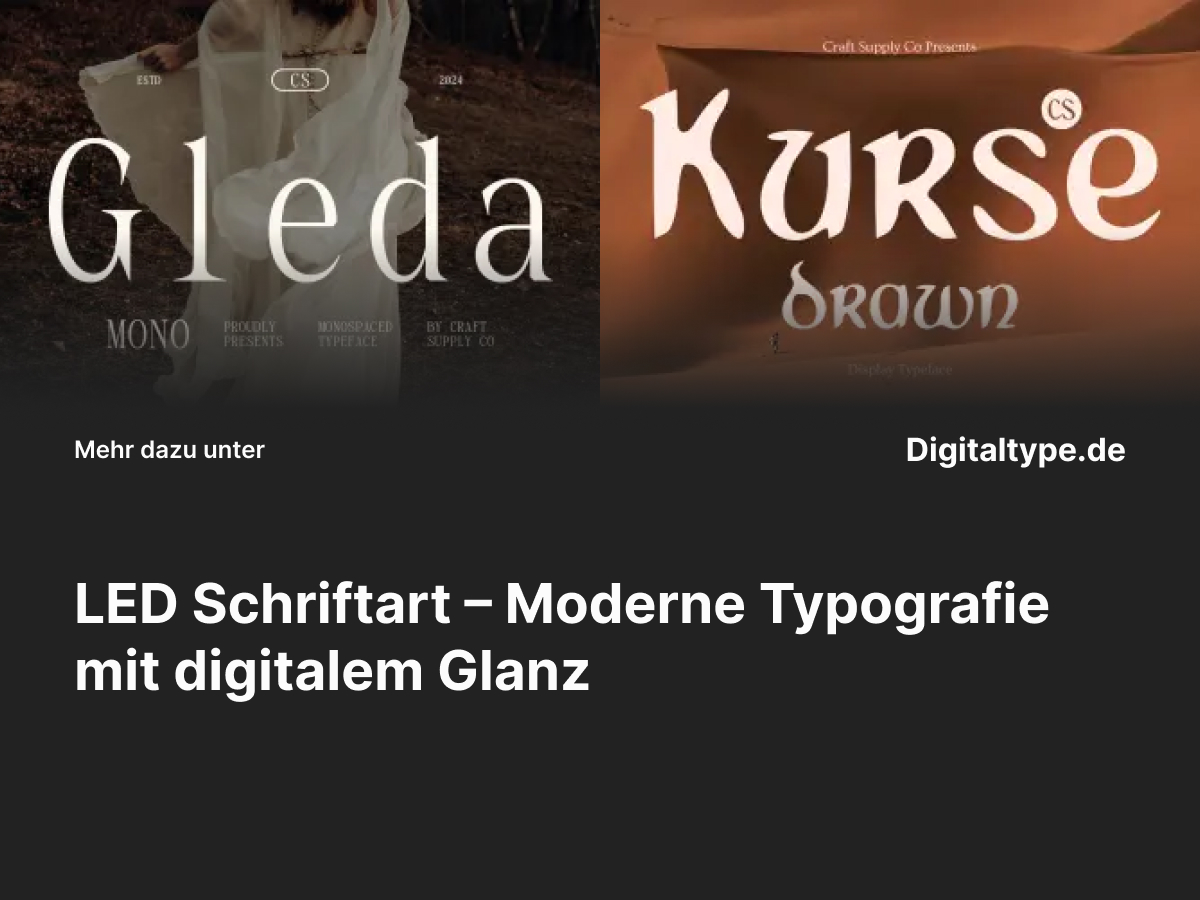
Eine LED Schriftart steht für Innovation, Technologie und futuristisches Design. Inspiriert von den leuchtenden Punkten und Linien digitaler Anzeigen, vermitteln diese Fonts ein modernes, technisches und professionelles Erscheinungsbild. Sie sind ideal für Projekte, die einen futuristischen Look, klare Struktur und Aufmerksamkeit durch leuchtende Formen suchen. In diesem Artikel stellen wir dir die besten LED-Schriftarten vor und zeigen, wie du sie optimal einsetzen kannst.
Was ist eine LED Schriftart?
Eine LED Schriftart imitiert den Stil elektronischer Leuchtdioden, wie man sie von Werbetafeln, Digitaluhren oder Displays kennt. Ihre Buchstaben bestehen häufig aus segmentierten Linien oder Punkten, die an leuchtende Pixel erinnern. Das Ergebnis: ein Schriftbild, das zugleich technisch, modern und aufmerksamkeitsstark wirkt.
LED Fonts eignen sich besonders für Branding, Gaming-Logos, Webdesigns oder Event-Plakate mit futuristischem Touch. Sie erzeugen Dynamik, Energie und ein Gefühl digitaler Innovation – perfekt, um moderne Zielgruppen anzusprechen.
Wann du LED Schriftarten verwenden solltest
- ✔️ Für Logos und Designs mit technologischem oder futuristischem Charakter.
- ✔️ In Gaming-, Musik- oder Event-Projekten, die mit Licht und Bewegung arbeiten.
- ✔️ Für digitale Werbungen, Displays und Webseiten mit modernem Erscheinungsbild.
- ✔️ In kreativen Branding-Projekten, die Innovation und Energie ausstrahlen sollen.
Eine LED Schriftart verleiht jedem Design ein leuchtendes, zeitgemäßes Erscheinungsbild – besonders effektiv in dunklen Farbschemata oder mit Neon-Effekten.
Die 7 besten LED Schriftarten für Designer
Hier sind sieben beeindruckende LED Schriftarten, die digitales Leuchten, klare Linien und kreative Energie perfekt vereinen. Jede davon eignet sich ideal für Projekte mit einem modernen, technologischen oder futuristischen Fokus.
1. CS Gleda Mono – Monospaced Font
CS Gleda Mono bietet ein präzises, technisches Design mit gleichmäßigen Abständen – ideal für LED-Displays und digitale Typografie. Perfekt für UI/UX-Projekte und moderne Branding-Konzepte.
2. CS Kurse – Drawn Font
CS Kurse kombiniert einen handgezeichneten Look mit klarer, futuristischer Struktur. Diese Schrift eignet sich hervorragend für kreative Designs mit digitalem Flair und modernem Ausdruck.
3. CS Gianluca – Messy Handwritten Font
CS Gianluca bringt eine organische Note in den LED-Stil. Ihr unregelmäßiger, handschriftlicher Charakter wirkt lebendig und modern zugleich – eine perfekte Mischung aus Technik und Persönlichkeit.
4. CS Ballard – Messy Handwritten Font
CS Ballard kombiniert künstlerische Energie mit digitalem Design. Ideal für plakative Schriftzüge, Poster oder Logos mit moderner Ästhetik.
5. CS Ramiro – Drawn Font
CS Ramiro überzeugt durch klare Linien und strukturierte Formen, die perfekt zu LED-Designs passen. Sie bringt Balance zwischen technischer Präzision und künstlerischem Ausdruck.
6. Harnold Pixel
Harnold Pixel ist eine echte Hommage an digitale Displays. Ihre pixelartige Struktur erinnert an Retro-LED-Schriften und ist perfekt für Projekte im Gaming-, Tech- oder Musikbereich.
7. CS Shane – Drawn Font
CS Shane bietet einen modernen Look mit geometrischen Details und klarer Struktur. Ideal für Branding, Poster oder digitale Interfaces mit einem Hauch futuristischer Energie.
Design-Tipps für LED Schriftarten
- 1. Verwende leuchtende Farben: Neonblau, Pink oder Grün betonen den LED-Effekt.
- 2. Setze dunkle Hintergründe ein: Sie lassen die Schrift leuchten und erzeugen Tiefe.
- 3. Nutze Glüheffekte sparsam: Zu viel Licht kann Lesbarkeit mindern.
- 4. Kombiniere mit klaren Sans-Serif-Schriften: Für ausgewogene, moderne Layouts.
Fazit: LED Schriftarten für modernes und futuristisches Design
Eine LED Schriftart ist die perfekte Wahl, wenn du deinem Design einen technologischen, modernen und leuchtenden Look verleihen willst. Ob für Branding, Werbung oder Social Media – LED Fonts ziehen garantiert Aufmerksamkeit auf sich.
Die vorgestellten Schriftarten vereinen Kreativität, Präzision und digitalen Stil. Sie helfen dir, Designs zu gestalten, die modern wirken und im Gedächtnis bleiben. Probiere sie aus und erlebe, wie sie deinem Projekt ein futuristisches Leuchten verleihen.